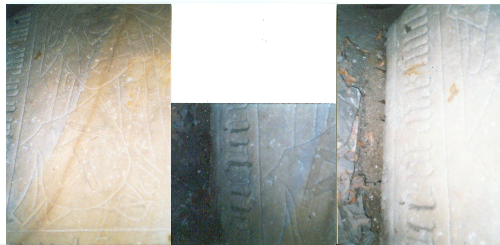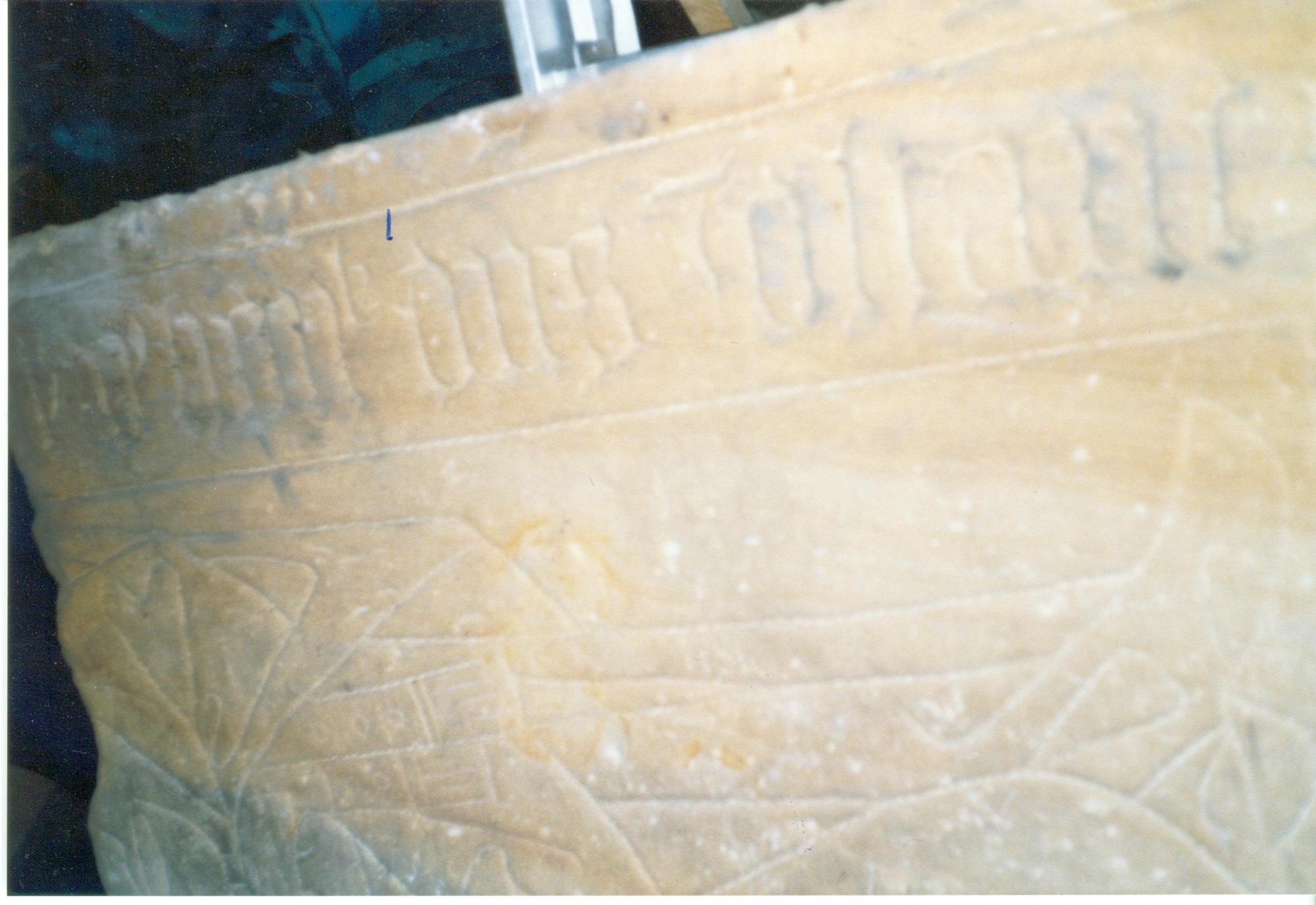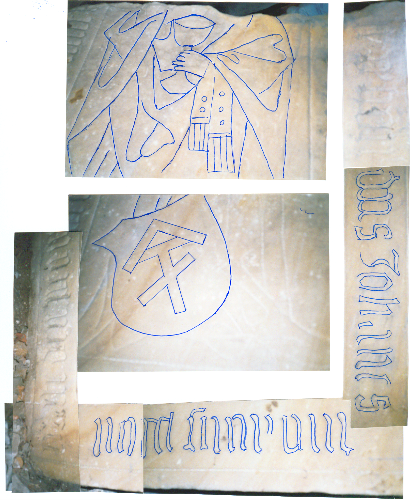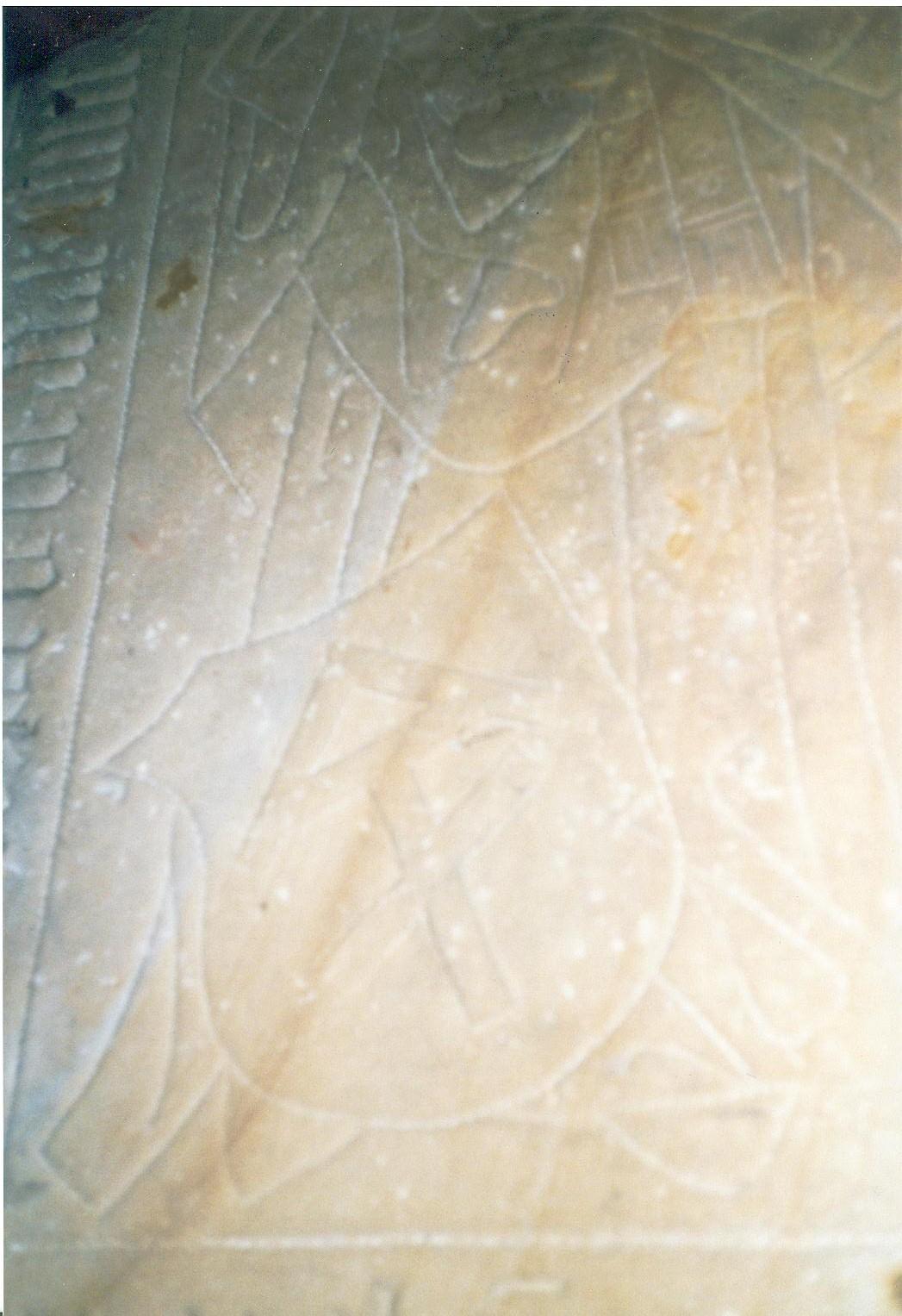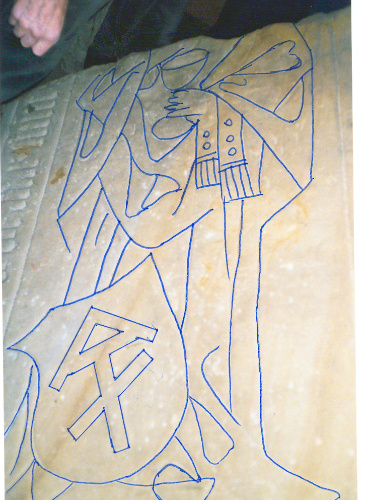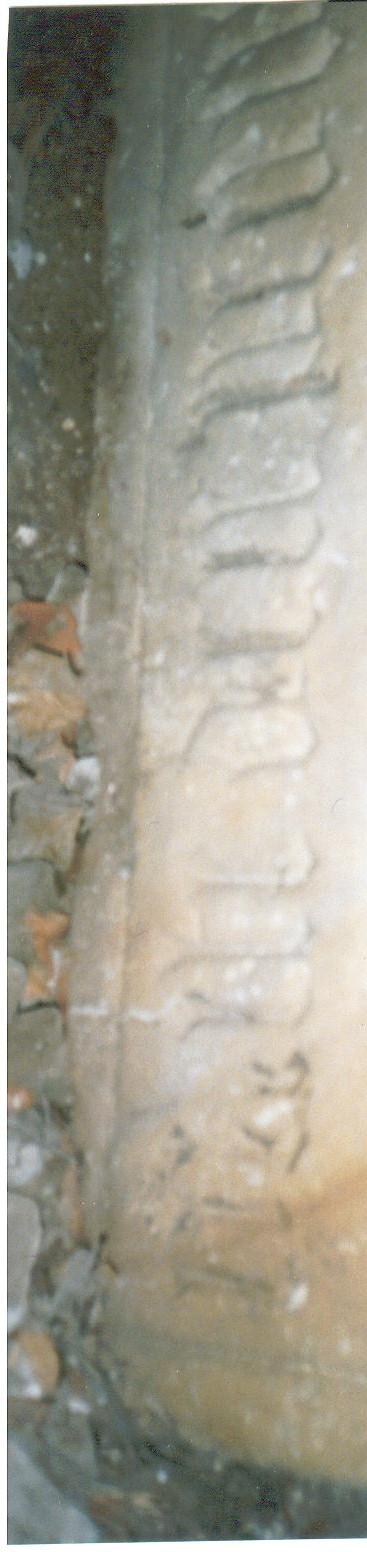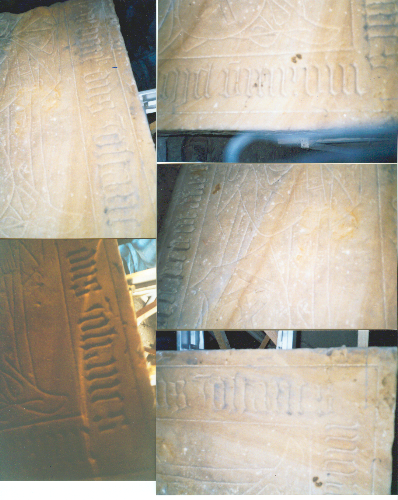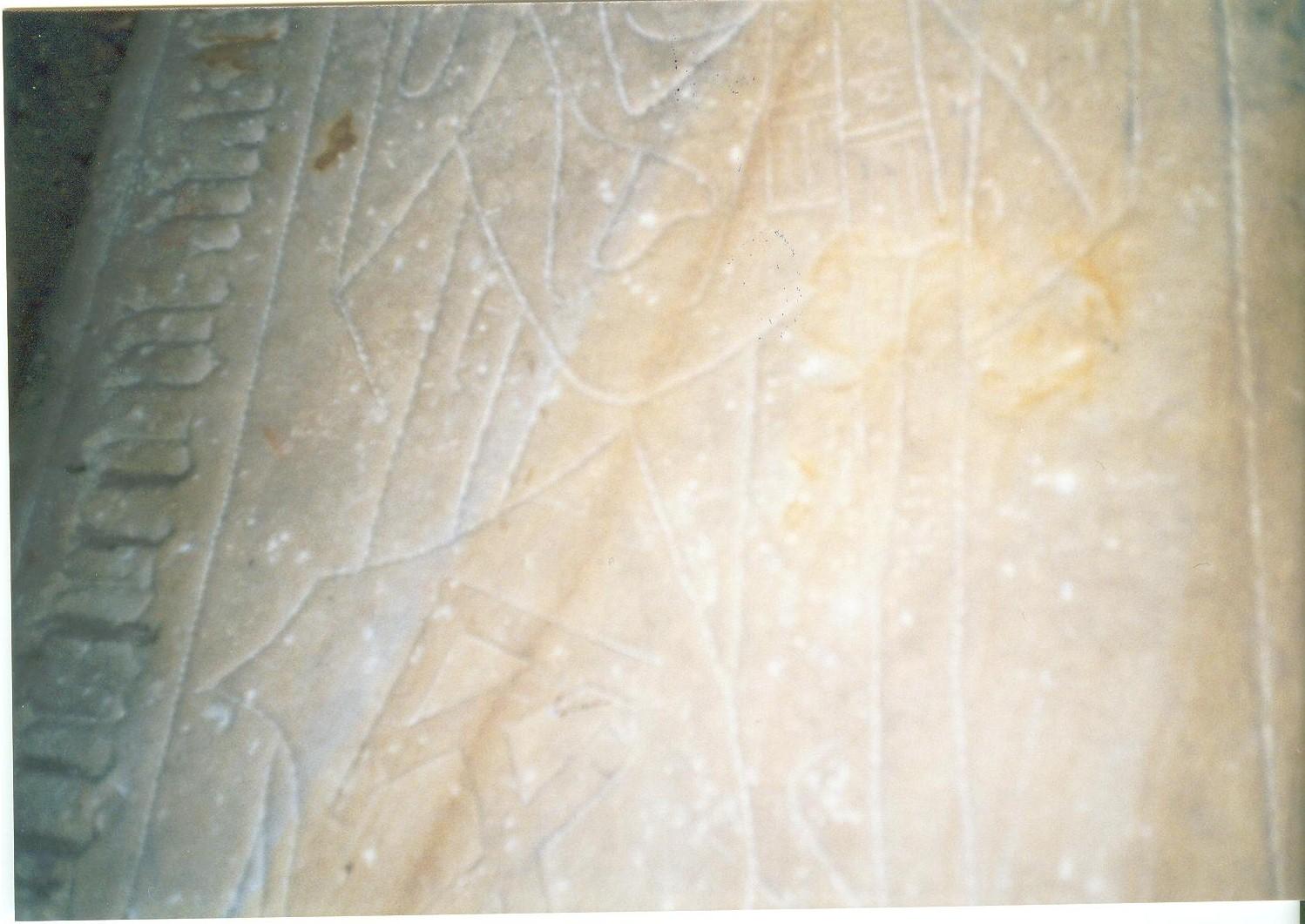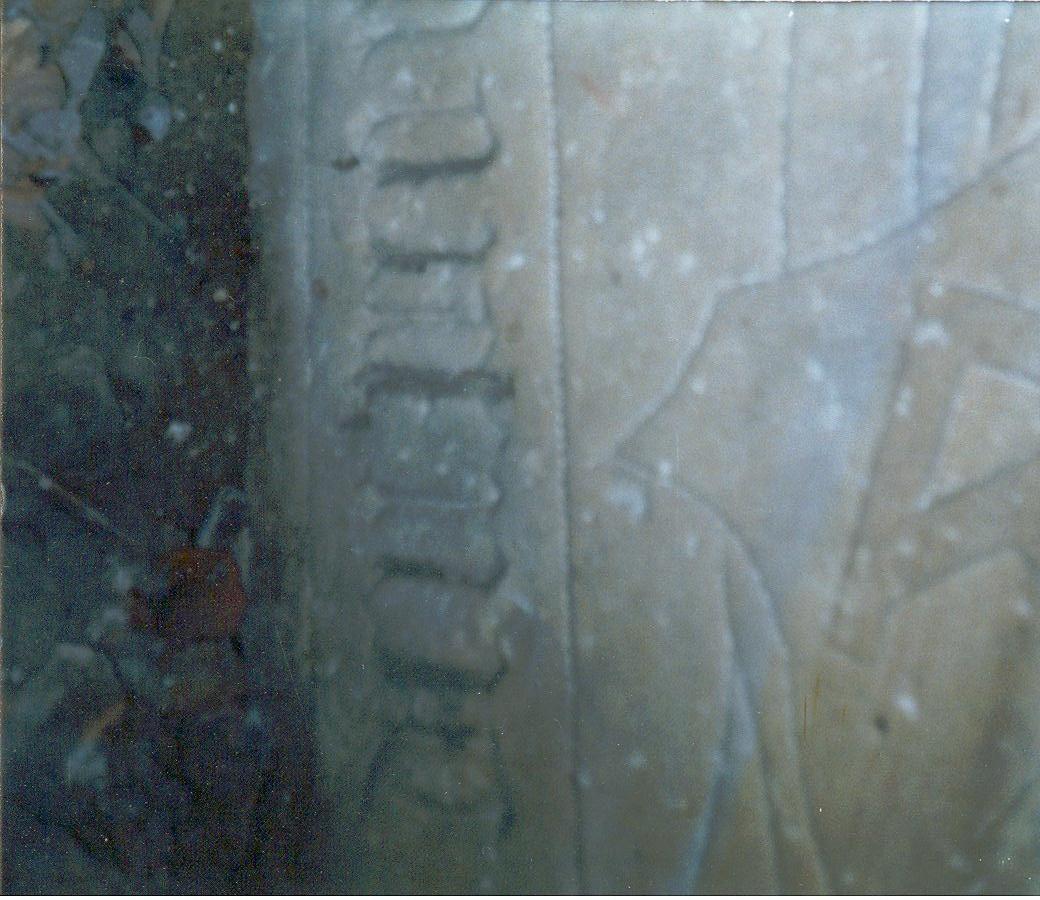
in unserer Kirche in Weißensee / Thür. befand sich sich vor einiger Zeit 2/3 eines Epitaphes. Inzwischen wurde er entsorgt und ich besitze nur einige wenige Fotos. Kann sie aber nicht bzw. schlecht lesen, vielleicht könnte ihr mir helfen.
Auf der dritten Abbildung von unten, nachgezeichnete gestürzte Zeile rechts, meine ich ein »Johanes« ausmachen zu können. Letzter Buchstabe vor dem Eigennamen wäre dann auch ein kleines s.
Das Wort vor "Johanes" ist "dns", ein sogenanntes Nomen sacrum. Steht für "d(omi)n(u)s". Dieser Titel zeigt wie Kelch und Manipel, dass es sich bei dem Inhaber des Epitaphs um einen Priester gehandelt hat. Wenn es die Bestandteile der Collagen auch mit besserer Auflösung gäbe, würde das die Entzifferung entscheidend erleichtern.
Wer "entsorgt" so etwas eigentlich? Das ist ja Barbarei! So ein Epitaph ist doch ein Kulturgut, das man leicht aufbewahren kann -- und wenn man es bloß, wie vielerorts zu sehen, einfach außen an die Kirchenmauer lehnt.
Bei Inschriften sind Bilder, auf denen der Blitz die Reliefs ausleuchtet, übrigens die schlechteste Möglichkeit der Dokumentation. Am besten verfertigt man, wenn ein Papierabklatsch nicht möglich ist, eine Abreibung, indem man Papier (Japanpapier oder einfach Butterbrotpapier) auf das Monument legt und mit Kohle, Ölkreide oder Bleistift darüber reibt.
Die Fotos hatte ich damals vor ca. 30 Jahren ganz fix mit einem normalen Fotoapparat gemacht, da war an eine digitale Kamera (in der DDR) nicht zu denken. Dann kam die Wende und es wurde in der Kirche "aufgeräumt", so verschwand einiges.